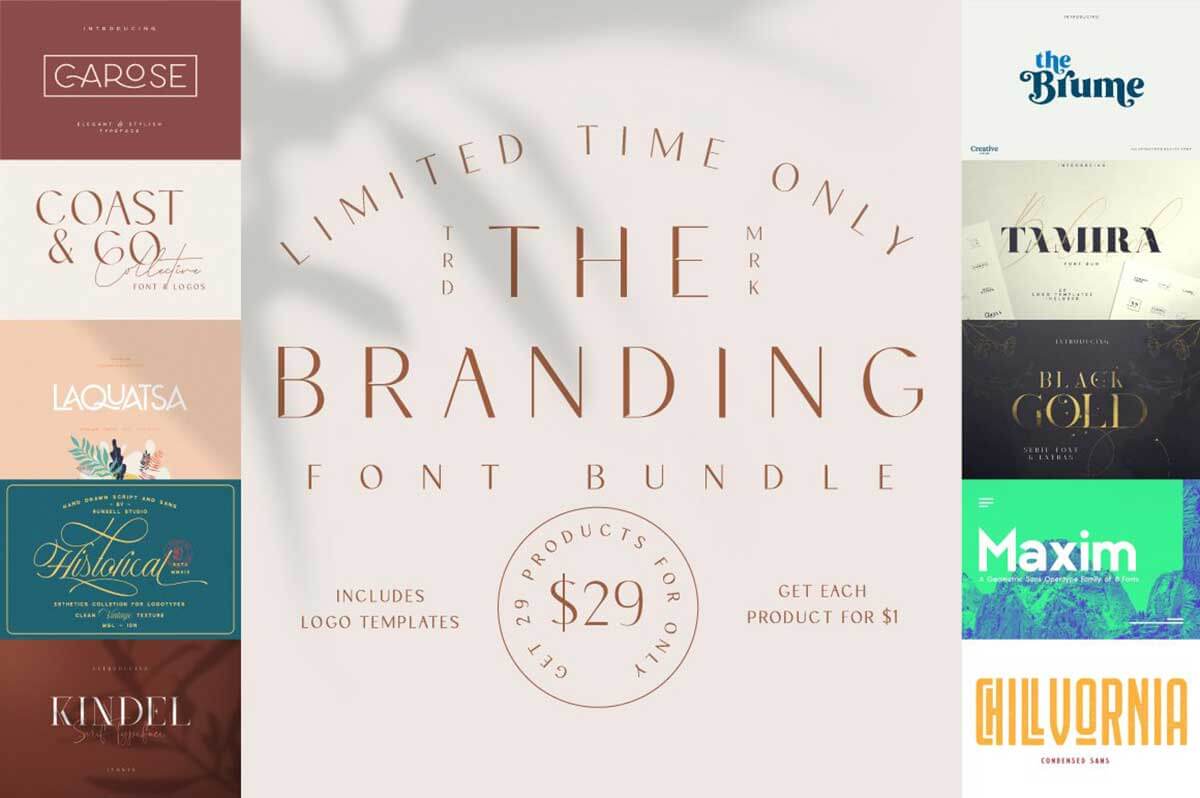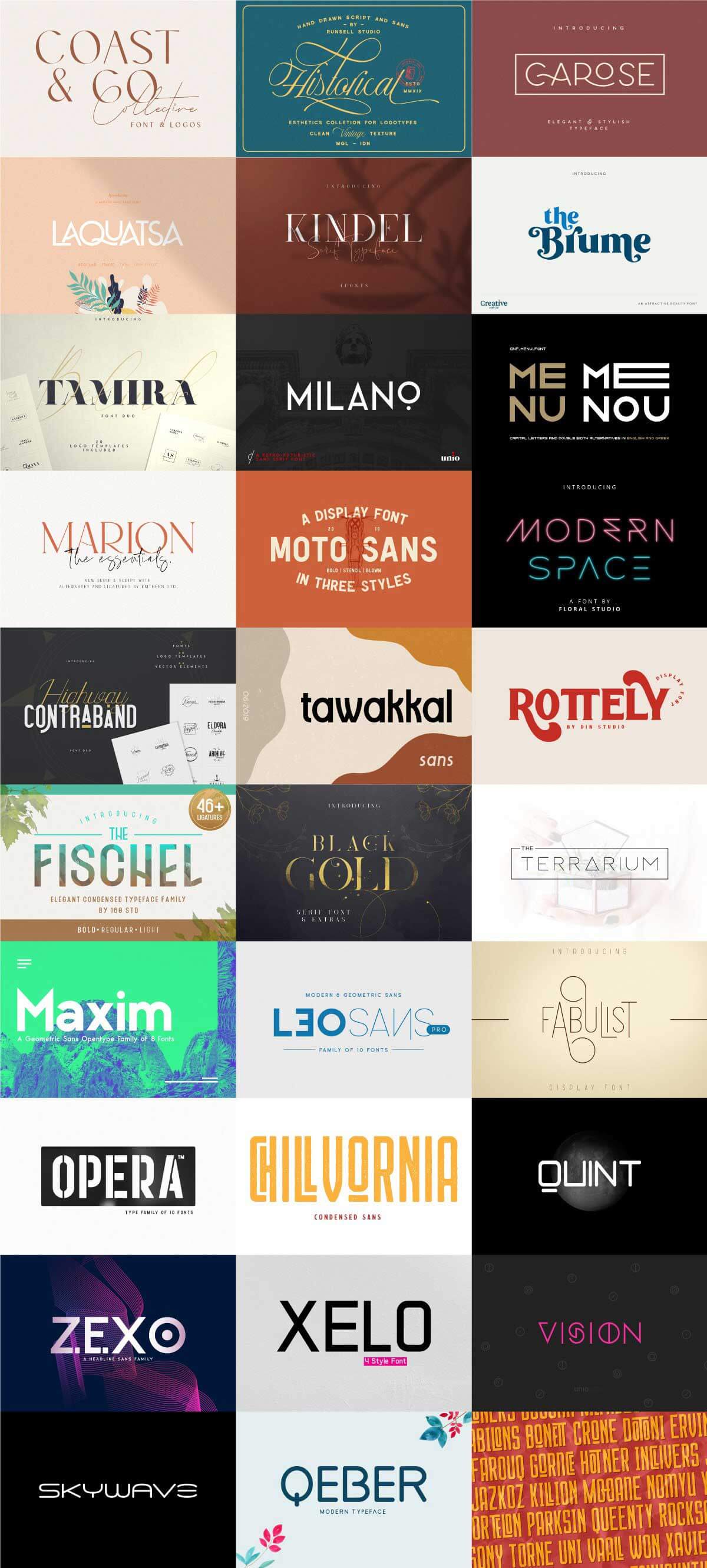
Pixel Surplusでは、フォント集「The Branding Font Bundle(ザ・ブランディング・フォント・コレクション)」が一ヶ月限定販売中です。
ブランディング向きのおしゃれな書体29セットを収録したコレクションです。Pixel Surplusでしか買えないオリジナルフォントや、イラストやロゴテンプレートなどのおまけもたくさん入っています。
「The Branding Font Bundle」の気になる内容
今回のバンドルの中で、私が特に気になるフォントはこちらです。
Black Gold – VPcreativeshop
複数の字形の中から組み合わせを選んだり、おまけの飾りを加えたりすることで多彩な表現が可能な「Black Gold」。ゴールドのテクスチャつきで、見本のように簡単に文字を金色にできます。
Brume – Creativemedialab
おしゃれな中にかわいらしさもあるフォント「Brume」。カフェやレストランのロゴ、メニューの見出しなどに使うといいアクセントになりそうです。
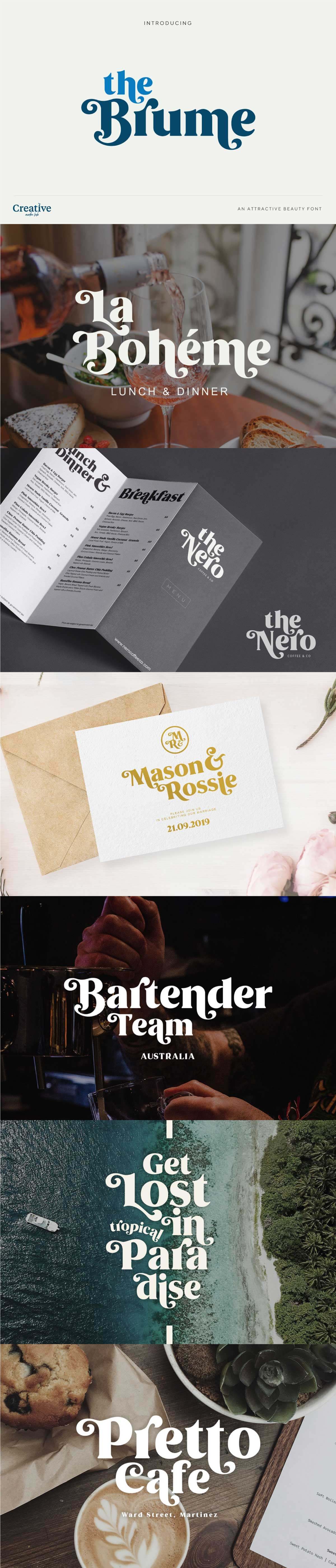
Belinda Tamira – VPcreativeshop
ところどころ線が消えた太めのセリフ体「Belinda Tamira」。見出しやロゴなどに大活躍しそうなおしゃれな書体で、多言語対応も高ポイントです。
Kindel Serif – VPcreativeshop
デザイン性が高いのに使いやすいセリフフォント「Kindel Serif」。連字もおしゃれにデザイン済みで、字形の違う4書体が入っています。
Modern Space – Floral Studio
無駄を限界まで削ぎ落としたシンプル・イズ・ベストなフォント「Modern Space」。女性向けはもちろん、クールな男性向け媒体にもハマるデザイン書体です。
Fabulist – VPcreativeshop
カジュアルで細めのデザイン書体「Fabulist」。さりげなくおしゃれなデザインが必要なときにピッタリです。
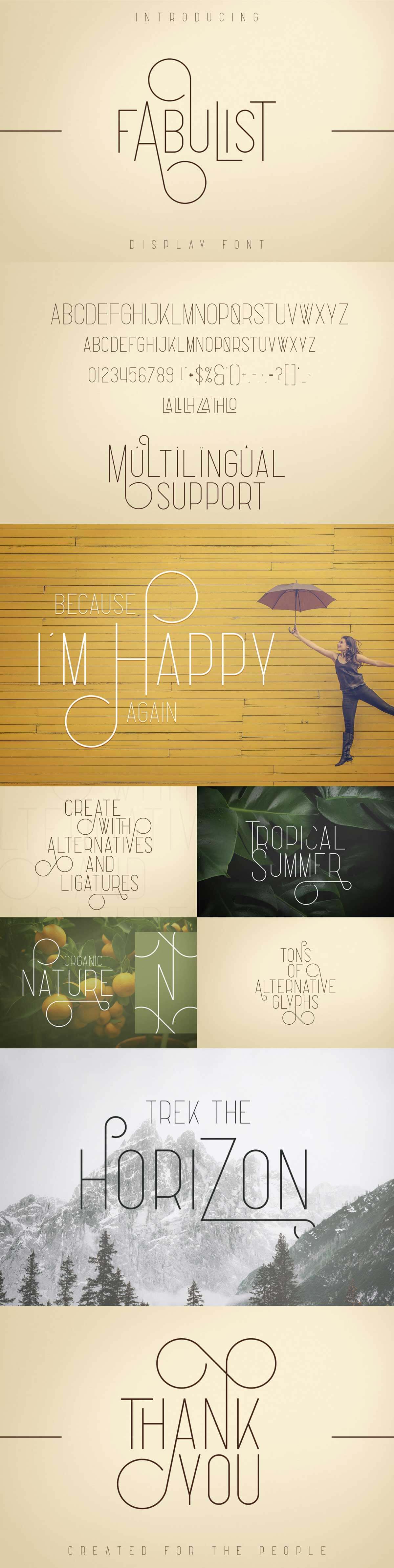
このほか合計29セットを収録しています。この記事で紹介できなかった書体はぜひ詳細ページから確認してくださいね。